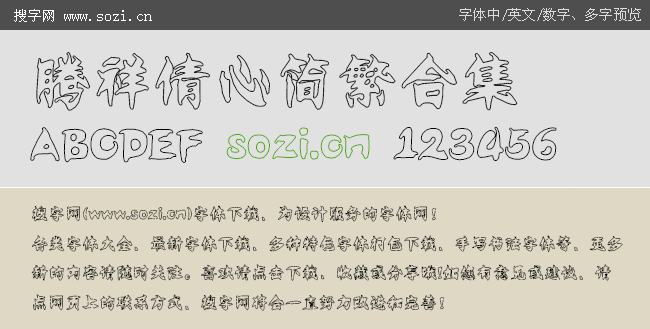
騰祥倩心簡(jiǎn)繁合集
搜字網(wǎng)提供一款騰祥倩心簡(jiǎn)繁合集中文藝術(shù)字體下載,騰祥倩心體是一款由手寫風(fēng)格的書法字體修改的藝術(shù)字體,字體大方得體,中間鏤空,效果非常漂亮,可以應(yīng)用于橫幅標(biāo)語(yǔ)、美術(shù)設(shè)計(jì)、宣傳海報(bào)、圖形設(shè)計(jì)等領(lǐng)域。